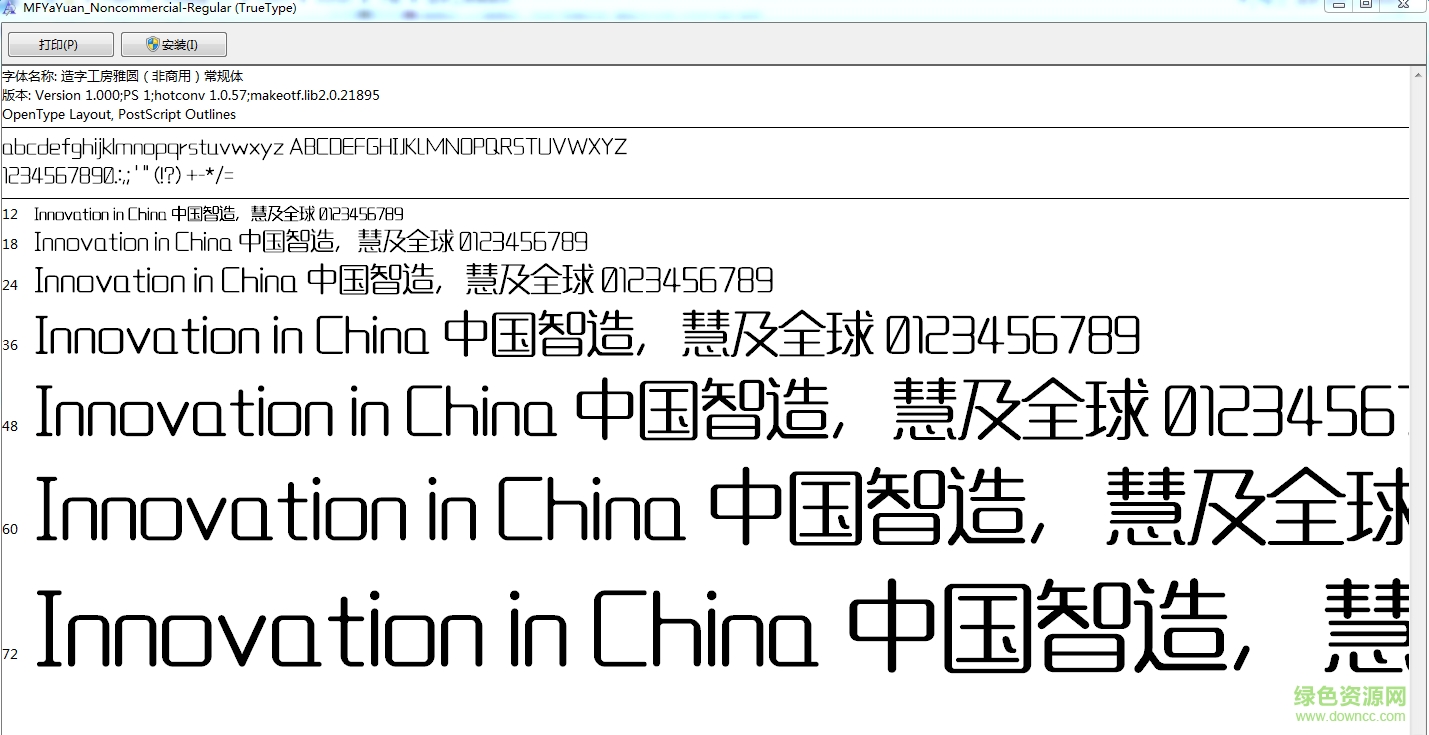
造字工房雅圓體是一款造字工房類簡約風(fēng)格字體軟件,雅圓體給人非常清新正式的感覺,整體效果比較醒目,適用于標(biāo)題推廣等,也深受廣大書法家的喜愛,還有更多好看字體盡情期待,歡迎到綠色資源網(wǎng)下載體驗(yàn)!
造字工房雅圓體是一款曲線柔美的中文簡體字體,其筆畫的設(shè)計(jì)在直線與曲線有著良好的平衡取舍關(guān)系,相互映襯,造就了與眾不同的字形特征,使其有著鮮明的視覺語言表現(xiàn)。適用于標(biāo)題、副標(biāo)題等視覺環(huán)境,尤其宜于女性品牌產(chǎn)品視覺形象的宣傳和推廣。